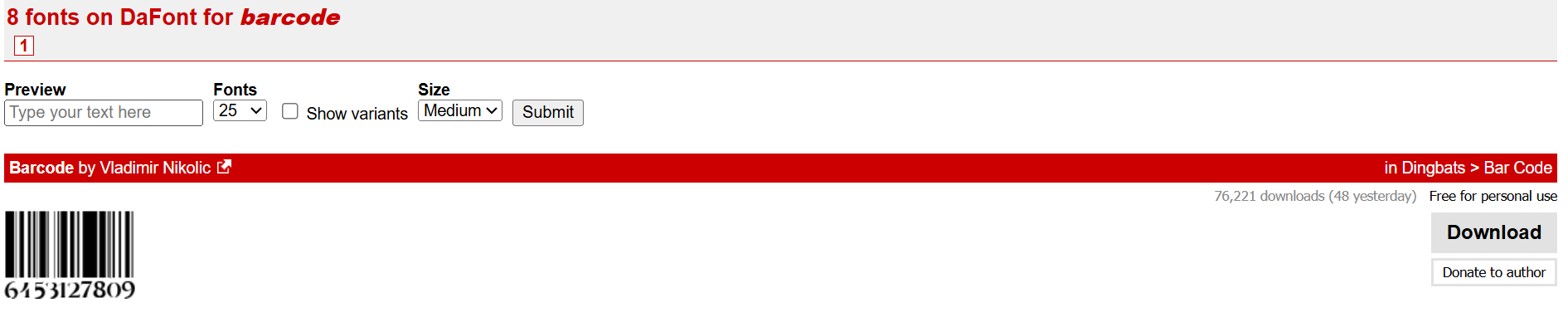
【Excel】エクセルのバーコードフォントの使い方(code39や128・jan13・設定・追加・ダウンロード方法)
エクセルでバーコードを作成したいとき、専用のソフトウェアを使わなくてもバーコードフォントを使えば簡単にバーコードを生成できることをご存知でしょうか?
バーコードフォントの設定方法とダウンロード方法を理解することで、在庫管理や商品管理に使えるバーコードをエクセル上で手軽に作成できるようになります。
この記事では【Excel】エクセルのバーコードフォントの使い方(設定・追加・ダウンロード方法)について解説していきます。
・バーコードフォントの仕組みと種類
・エクセルでバーコードフォントを設定して表示する方法
・Code39・Code128などの主要バーコード形式の使い方
エクセルのバーコードフォントとは何か・仕組みを理解しよう
バーコードフォントとは、文字や数字をバーコードのパターンに変換して表示する特殊なフォントです。
通常のフォントが文字を「読める形」で表示するのに対し、バーコードフォントは文字を「スキャナーで読み取れるバーとスペースのパターン」に変換して表示します。
バーコードフォントを使えば、専用のバーコード生成ソフトなしにエクセルのセルに文字列を入力するだけでバーコードを表示できます
バーコードフォントが使える場面
バーコードフォントが特に役立つ場面として、在庫管理・商品管理・資産管理・入荷・出荷ラベルの作成などが挙げられます。
下記のような商品管理表にバーコードを追加することで、スキャナーで読み取り可能な管理シートを作成できます。
商品名 商品コード バーコード 在庫数
桜餅 SW001 (バーコード表示) 50
カツオ KT002 (バーコード表示) 25
マグロ MG003 (バーコード表示) 18
ボルト BT004 (バーコード表示) 300
バーコードフォントを設定したセルに商品コードを入力するだけで、バーコードが自動的に表示されます。
主なバーコードの種類と用途
バーコードにはいくつかの規格があり、用途によって使い分けます。
Code39は英数字と一部の記号を扱えるシンプルな規格で、社内管理用途に広く使われています。フォントで対応しやすく最も手軽に使えます。
Code128はCode39より高密度でより多くの文字を扱えます。物流・在庫管理などビジネス用途で広く使われています。
EAN・JANコードはスーパーやコンビニの商品に貼られている13桁の規格です。専用のフォントまたは計算式が必要です。
QRコードは2次元コードのため通常のバーコードフォントでは対応できず、専用のアドインが必要です。
社内管理目的であればCode39が最もシンプルで導入しやすい選択肢です。
バーコードフォントの限界と注意点
バーコードフォントは手軽ですが、いくつかの制限があります。
印刷品質によっては読み取りエラーが発生することがあります。また使用するフォントによっては対応する文字の種類に制限があります。
商品販売用の正式なJANコードを使いたい場合は、GS1 Japanへの登録と専用ソフトウェアの使用が必要です。
【操作のポイント】バーコードフォントは文字をバーとスペースのパターンに変換する特殊フォント。社内管理用途ならCode39が最もシンプルで導入しやすい。正式な商品バーコードには専用システムが必要。
エクセルでバーコードフォントを設定して表示する方法
バーコードフォントのインストールが完了したら、エクセルでバーコードを表示する設定を行います。
Code39を例に具体的な手順を確認しましょう。
Code39バーコードを表示する基本手順
たとえば「BT004」というコCode39バーコードを表示するには、バーコードにしたい文字列の前後にアスタリスク(*)を付ける必要があります。
これはCode39の規格でスタート・ストップキャラクターとしてアスタリスクが使われているためです。ードのバーコードを表示する場合、セルに「*BT004*」と入力します。
次にそのセルを選択し、フォントを「Free 3 of 9」などのCode39フォントに変更すると、バーコードが表示されます。
Code39ではアスタリスクを前後に付けることが必須であり、付け忘れるとバーコードリーダーで正しく読み取れません
数式でアスタリスクを自動付加する方法
商品コードが別のセルに入力されている場合は、数式を使って自動的にアスタリスクを付加する方法が便利です。
A列に商品コードが入力されている場合、バーコード表示用のセルに以下の数式を入力します。
="*"&A2&"*"
この数式によりA2セルの値の前後に自動的にアスタリスクが付加されます。
このセルのフォントをバーコードフォントに変更すればバーコードが表示されます。
下記のように数式を使うことでA列のコードを変更するだけで自動的にバーコードが更新されます。
商品名 商品コード(A列) バーコード用数式(B列)
ネジ NJ001 =”*”&A2&”*” → *NJ001*
マシュマロ MS002 =”*”&A3&”*” → *MS002*
カボチャ CV003 =”*”&A4&”*” → *CV003*
アボカド AV004 =”*”&A5&”*” → *AV004*
バーコードのサイズと印刷設定を調整する方法
バーコードを正しく読み取れるようにするには、フォントサイズと印刷設定を適切に調整することが重要です。
バーコードフォントのサイズは一般的に30〜48ポイント程度が読み取りに適しています。
小さすぎるとバーの幅が細くなりすぎてスキャナーで読み取れなくなるため、実際にスキャナーで読み取りテストを行ってから運用することをおすすめします。
印刷時は「高品質印刷」モードを選択し、バーの境界がはっきり印刷されるように設定することが読み取り精度向上のポイントです。
【操作のポイント】Code39は文字列の前後に「*」を付けてからバーコードフォントを適用。数式「=”*”&A2&”*”」で自動付加が便利。フォントサイズは30〜48ポイントを目安に設定し実際にスキャナーで読み取りテストをしよう。
エクセルのActiveXコントロールを使ってバーコードを作成する方法
バーコードフォントを使う方法のほかに、エクセルに標準搭載されているActiveXコントロールの「Microsoft BarCode Control」を使ってバーコードを作成する方法もあります。
Microsoft BarCode Controlの挿入方法
「開発」タブ→「挿入」→「ActiveXコントロール」→「その他のコントロール」をクリックします。
コントロールの一覧から「Microsoft BarCode Control」を選択してOKをクリックし、シート上にドラッグして配置します。
配置したコントロールを右クリックして「プロパティ」を開くと、バーコードの種類・値・サイズなどを設定できます。
Microsoft BarCode ControlはOffice 2010以降の一部エディションに標準搭載されていますが、環境によっては利用できない場合があります
セルの値とバーコードをリンクさせる方法
ActiveXのバーコードコントロールをセルの値と連動させるには、VBAを使う方法が一般的です。
コントロールを右クリック→「コードの表示」でVBAエディターを開き、以下のようなコードを入力することでA1セルの値が変わるたびにバーコードが自動更新されます。
Private Sub Worksheet_Change(ByVal Target As Range)
If Target.Address = "$A$1" Then
BarCodeControl1.Value = Target.Value
End If
End Sub
このコードはA1セルの内容が変更されるたびにバーコードコントロールの表示値が自動更新される仕組みです。
バーコードフォントとActiveXコントロールの使い分け
・Code39の設定方法:文字列の前後に「*」を付けてからバーコードフォントを適用。数式「=”*”&A2&”*”」で自動付加が便利
・印刷設定:フォントサイズは30〜48ポイントを目安に設定。高品質印刷モードで出力し実際にスキャナーで読み取りテストを行う
・ActiveXコントロール:「開発」タブから追加可能。VBAと組み合わせることでセル値と連動したバーコード表示ができる
・トラブル対処:表示されない場合はフォント再インストールとエクセル再起動。別PCとの共有はPDF出力が最も確実
バーコードフォントを活用することで、専用ソフトを使わずにエクセルだけで実用的なバーコード管理シートを作成できます。
まずはCode39フォントをダウンロードして、シンプルな商品管理表でバーコード表示を試してみましょう。